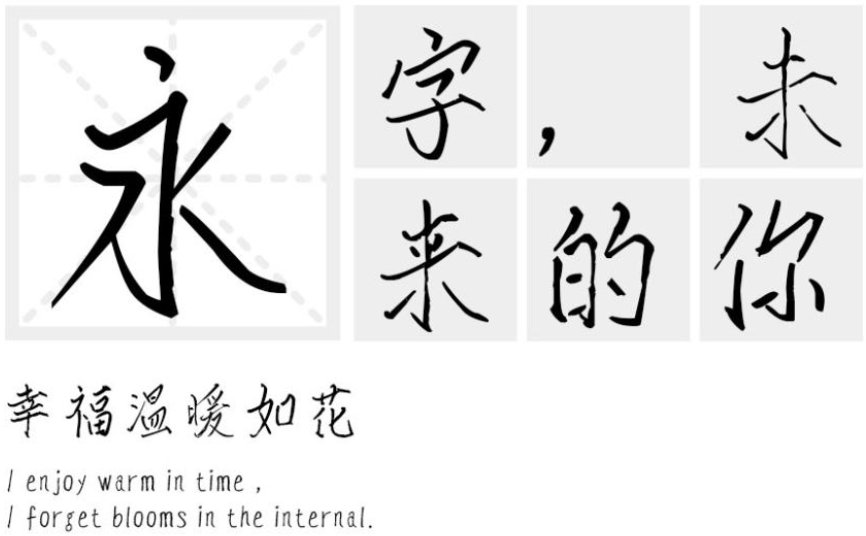
汉标瘦金简体是一款非常好看有趣的电脑汉标中文字体。这款字体书写流畅,看上去非常的舒适,就好像是自己书写的一样,非常好看;
瘦金书本来偏瘦,在实际版面中易虚化而不易远观,这款字体加粗了笔画,笔形和结构高度稳定,易读性强。其风格雍容高雅,适用于文化类的宣传设计,以及商业类品牌的广告和产品包装设计。
字体展示:
字体类别:手写字体
适用场景:广告、印刷、正文